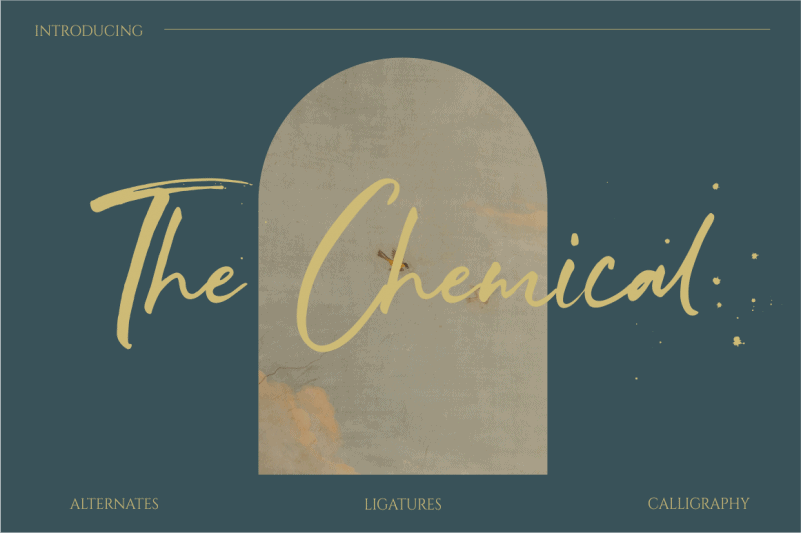
The Chemical Brush Font – Download Grátis
A novidade vem em forma de uma fonte casual chamada The Chemical Brush Font, criada por ReyreyBlue para a categoria de fontes Script. Este não é apenas mais um design elegante; ele traz uma atmosfera descontraída e quase hipster ao seu projeto. Com traços aveludados e fluidos, esta fonte se destaca como uma opção versátil, adequada tanto para criações de texto casual quanto para elementos gráficos cheios de personalidade. Perfeita para aqueles que buscam algo mais autêntico e menos formal em suas aplicações digitais. Nesta série de Script Fonts, a The Chemical Brush Font promete oferecer um toque único à sua obra, combinando facilmente com outros estilos e cores para criar designs originais. Não perca esta oportunidade de dar uma revolução aos seus projetos visuais com uma fonte cheia de personalidade.